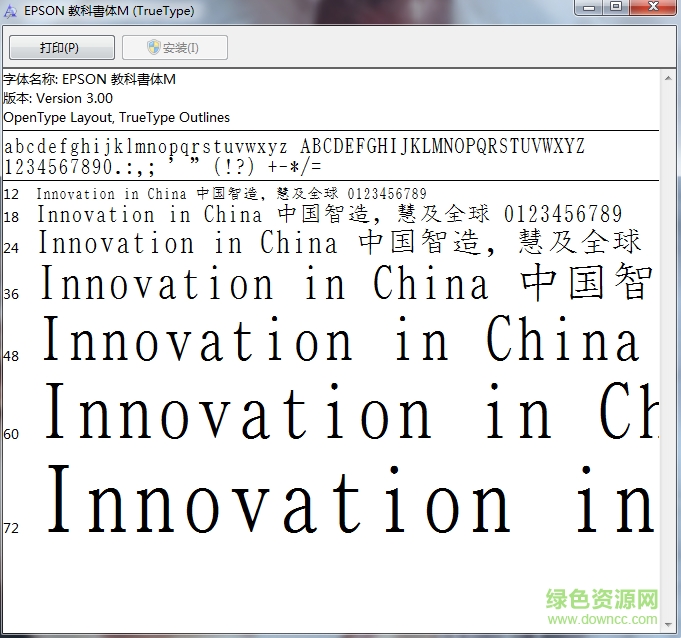
愛普生教科書體是一款愛普生打印機(jī)中常用到的教科書式的字體,端正嚴(yán)謹(jǐn),支持繁體輸入,讓你的文字排版、平面設(shè)計(jì)、廣告創(chuàng)意更顯大氣莊嚴(yán)之感,歡迎大家在綠色資源網(wǎng)免費(fèi)下載!
愛普生教科書體需在繁體狀態(tài)下使用,簡(jiǎn)體中文會(huì)使部分漢字無法顯示。